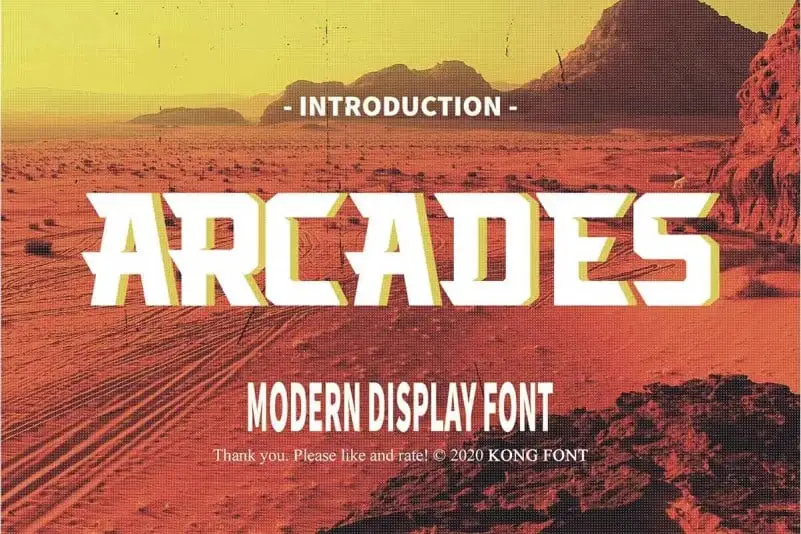
Arcades Display Font – Download Grátis
A fonte Arcades Display é perfeitamente adaptada para uso como tipo à mostra, uma opção ideal quando você deseja criar cartões de convite encantadores para casamentos, aniversários e outros dias especiais. Suas letras e números são uma coleção versátil que se adequa a diversos projetos, desde logotipos até design de marca, criação de logos, arte digital, camisetas e roupas, cartazes, revistas, sinais, propaganda e muito mais. Este tipo elegante proporcionará um toque único e encantador a suas criações. Não importa qual projeto estiver trabalhando, Arcades Display é uma excelente escolha para complementar sua marca ou aniversário especial.